12 Font Canva Aesthetic, Bikin Desain Makin Outstanding
Tipografi font Canva memengaruhi keelokan desain grafis.
Font aesthetic Canva tersedia gratis maupun berbayar, dapat disesuaikan dengan tujuan penggunaannya.
Daftar font aesthetic Canva meliputi Migra, Anaktoria, Kollektif, Megrim, Linux Biolinum, hingga VAL.
Desain cakep tentu kurang lengkap tanpa adanya tipografi. Seni memilih teks dalam desain grafis ini gak bisa dilakukan sembarangan, lho! Sebab, penggunaan font yang tepat akan memengaruhi keelokan desain. Misalnya, membuat ucapan selamat menggunakan font Chiller, kan, jadi horor, ya.
Memilih font bisa memakan waktu lama. Untungnya, ada berbagai opsi font aesthetic Canva yang tersedia gratis maupun berbayar. Gak cuma informatif, desainmu pun akan makin ciamik dan terasa lebih 'hidup'. Tinggal atur deh tata letaknya.
Daftar font aesthetic Canva
Sebelum memilih font, aturan terpenting yang harus kamu lakukan adalah mengetahui tujuan dari penggunaannya, apakah untuk logo brand anak muda kekinian atau instansi formal. Keduanya membutuhkan gaya yang berbeda, sehingga wajib untuk memperhatikan tipografinya.
Prinsipnya, fonts terbagi menjadi dua jenis utama yakni Serif dan San-Serif. Serif memiliki ujung bervariasi, seperti meliuk atau melingkar, alias berkaki, misalnya Times New Roman. Sebaliknya, Sans-Serif merupakan font yang memiliki ujung tegas dan terkesan modern atau gak berkaki, contohnya Helvetica.
Nah, fungsi pemakaiannya pun berbeda. Penggunaan Serif modern kini banyak dijumpai pada tipografi estetik. Adapun Sans-Serif sering diperuntukkan pada tulisan dengan tujuan yang mudah dibaca. Di Canva, keduanya bisa kamu temui dengan mudah. Font aesthetic Canva tersebut pun bisa kamu kombinasikan untuk desainmu.
1. Migra
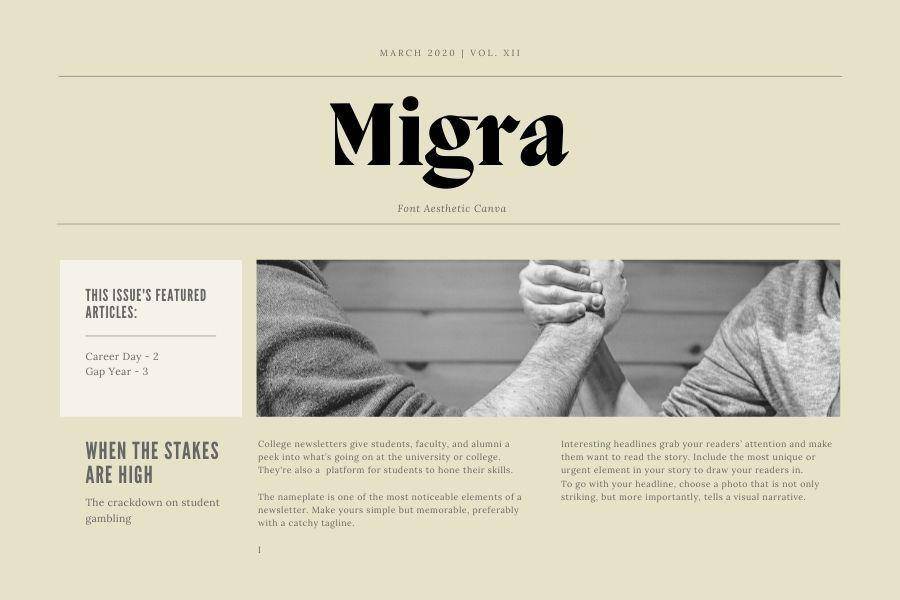
Mengawali list font aesthetic Canva dengan jenis serif yang 'old but gold'. Font ini persis yang digunakan pada koran jadul. Meski memiliki kaki, Migra masih mudah dibaca dan cocok untuk badan teks yang membutuhkan kesan tradisional. Ada dua bobot font tersedia, lalu bisa menerapkan aturan italic, bold, maupun underline juga.
2. Anaktoria
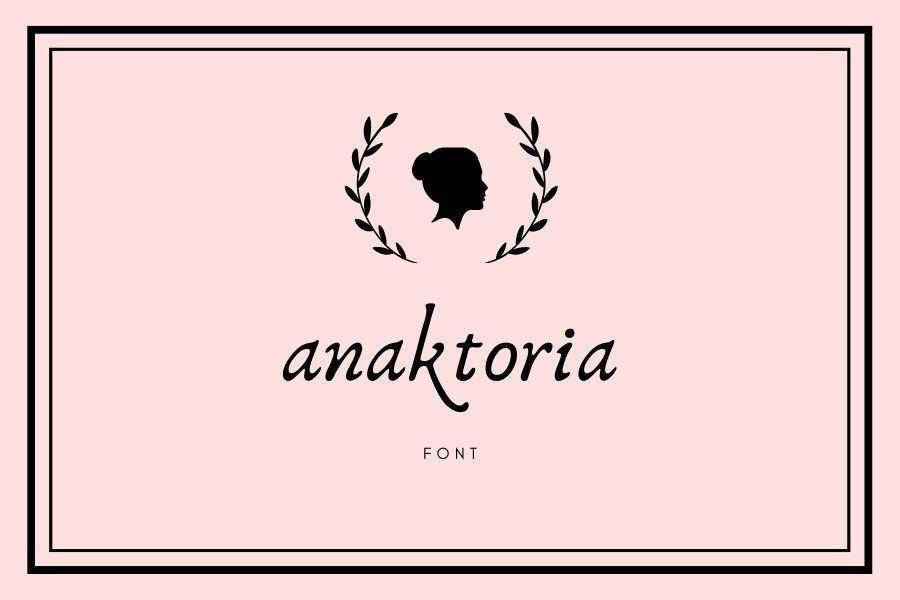
Butuh handwritting font yang gak neko-neko? Anaktoria bisa kamu gunakan untuk desainmu. Font ini mengusung karakter huruf bersambung, tapi gak bersambung mirip tulisan tangan. Anaktoria pun memiliki aksen yang bisa meningkatkan visual desain.
3. Kollektif
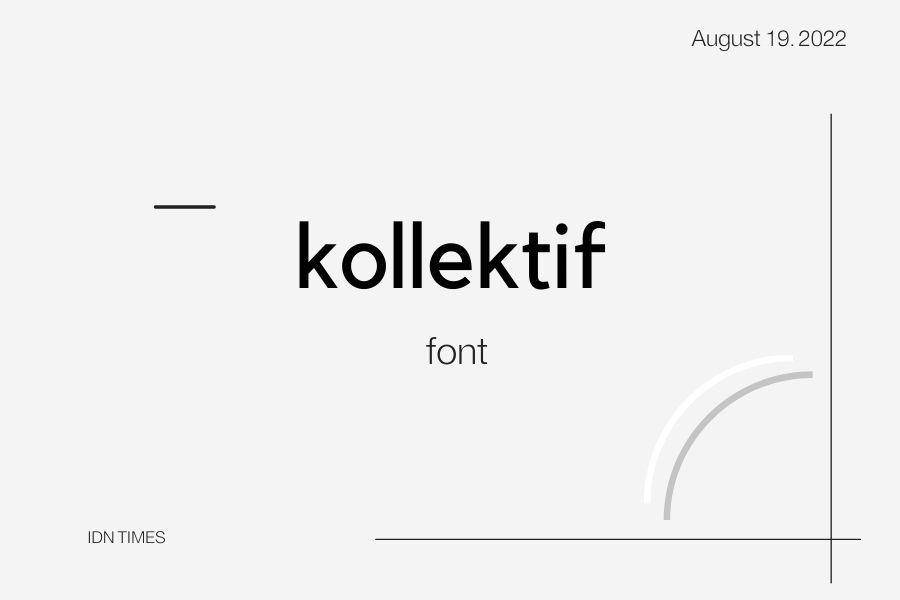
Font bersih dan minimalis ini sangat nyaman dipandang. Dengan ujung tegas tanpa ekor, Kollektif memberikan kesan to the point. Mudah dibaca, tapi gak kaku-kaku amat, mau dibuat judul, head, ataupun badan teks, Kollektif tetap oke.
4. Megrim
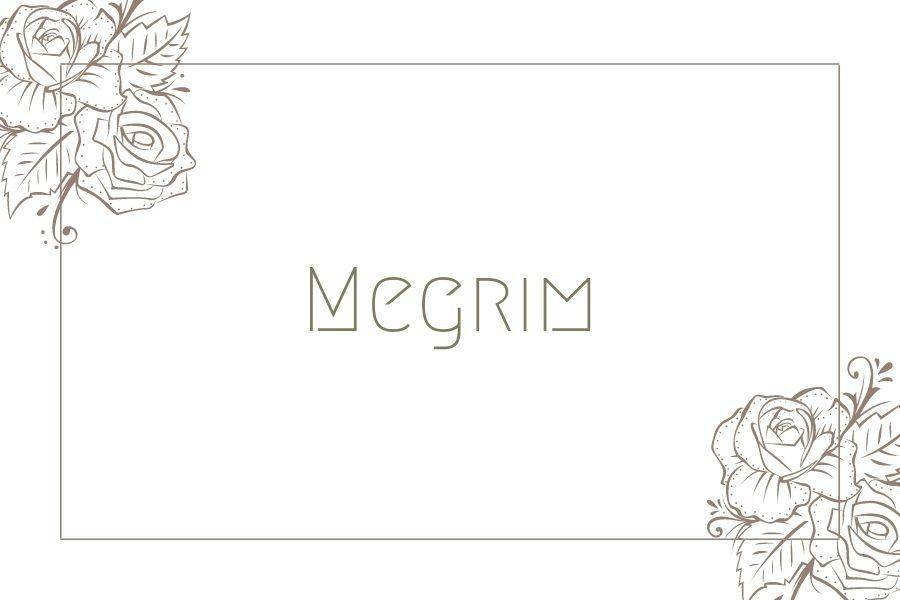
Ingin font unik, tapi tetap mudah dibaca? Megrim oke untuk dipadukan dengan gambar maupun ilustrasi. Font ini mengusung struktur geometris yang tegas, tapi memiliki tambahan style yang bisa membuat desainmu lebih unik. Cocok untuk judul yang menuntut atensi lebih.
5. Linux Biolinum
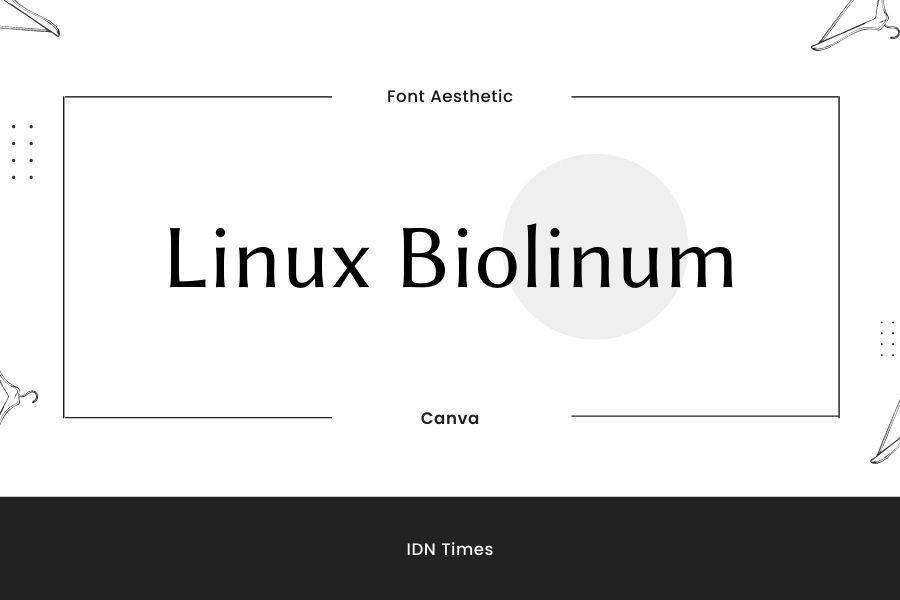
Desain font ini merupakan jenis Sans-Serif dengan layar berbasis modul. Bentuknya memanjang dan tertutup, serta memiliki x-height yang tinggi. Secara default, font tersusun rapat sehingga terkesan slim dan gak memakan ruang. Spasinya membuat kesan renggang dan mudah dibaca.
6. VAL
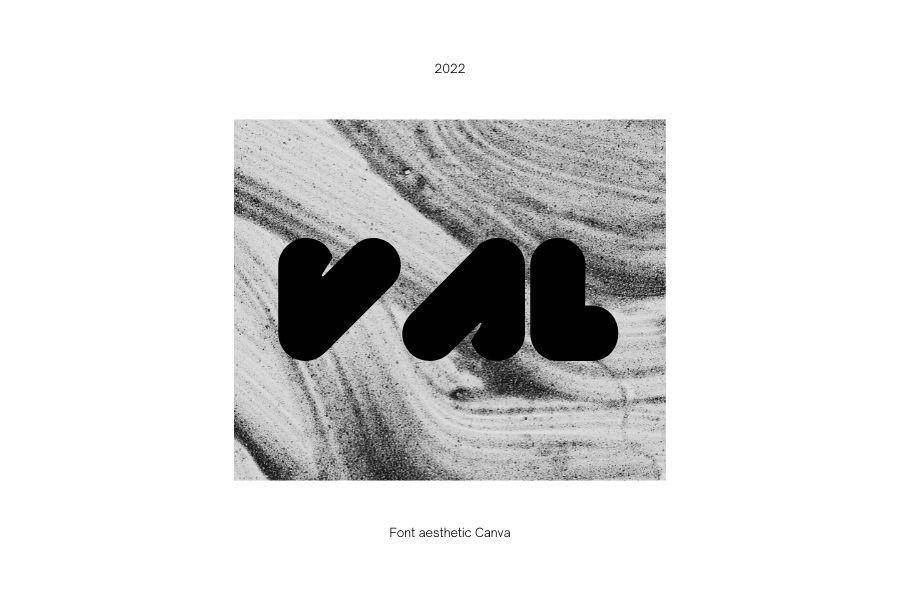
Dari namanya, sekilas bikin teringat brand produk laki-laki, gak, sih? Well, font ini bersifat modern, minimalis, dan membulat. Semakin unik, pembuat menyisipkan seni tulisan dengan memiringkan sebagian sisi huruf yang cocok jadi pilihan font aesthetic Canva.
7. Giaza
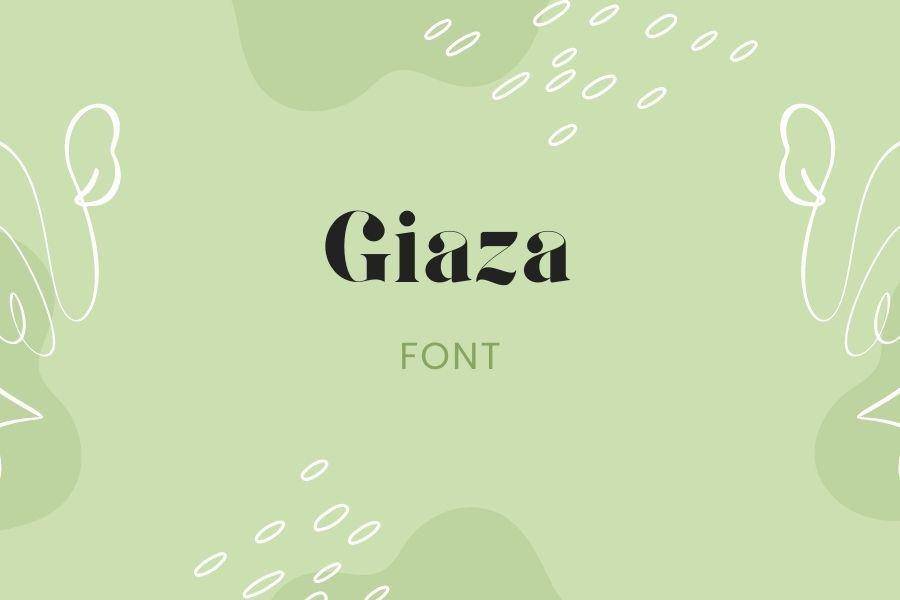
Butuh font aesthetic Canva yang masuk jenis Serif, tapi gak kuno? Giaza bisa jadi solusi. Giaza merupakan jenis huruf terbaca dan bersih. Mengonsep huruf dengan ketebalan sisi yang berbeda, cocok untuk memberikan kesan tegas, tapi gak kaku. Ciamik, bukan?
8. Dreaming Outloud
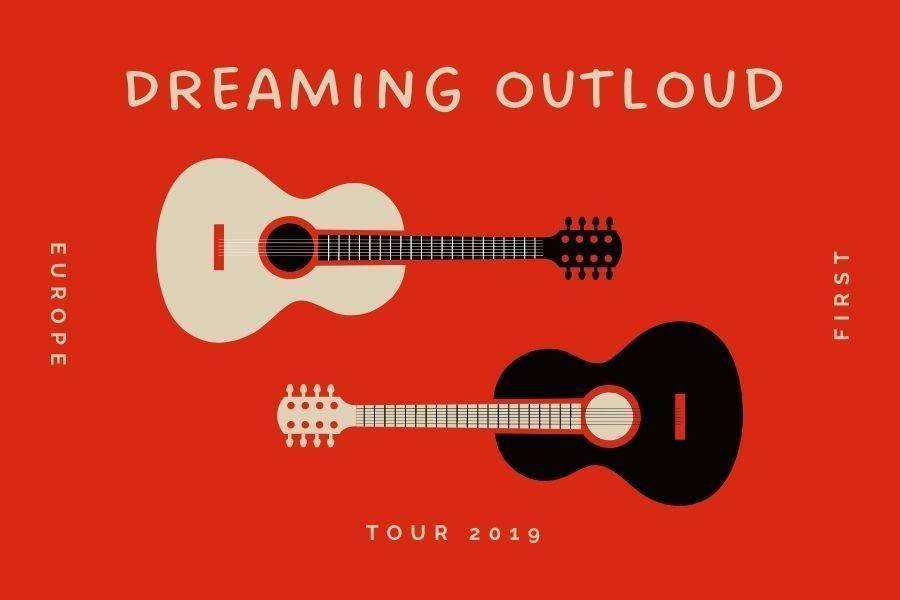
Poster musik sering menggunakan font sesuai genre konsernya. Nah, font Dreaming Outloud merupakan pilihan yang cocok. Merupakan font kapital, membuat masing-masing huruf memiliki tinggi dan lebar yang sama. Meski terkesan gak formal, font ini tetap memberikan kesan jelas.
9. Bugaki
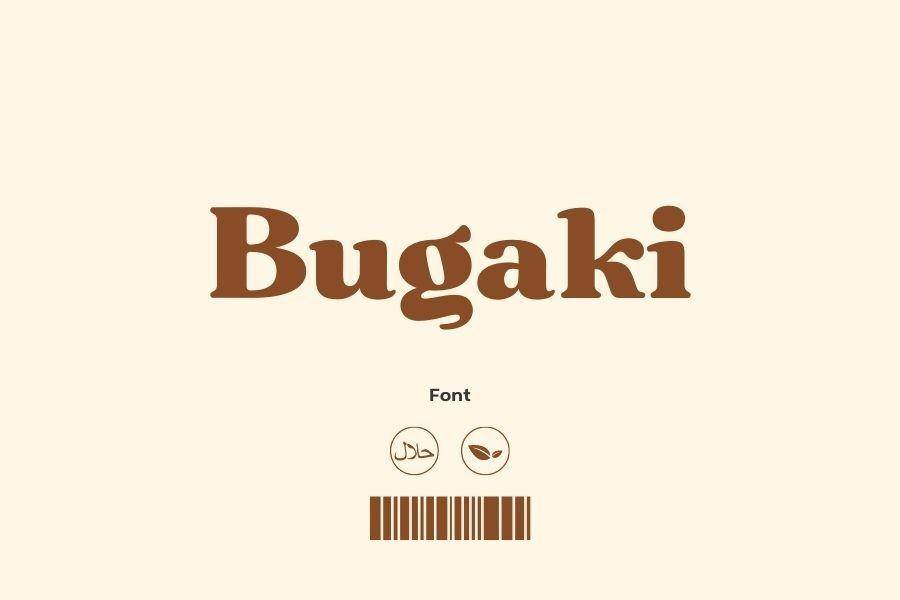
Ada juga font aesthetic Canva yang memberikan desain berbeda saat digunakan dalam huruf kapital dan huruf kecil, salah satunya Bugaki. Font ini membawa kesan bold, tetapi dengan sentuhan tebal tipis yang menawan. Bentuk huruf tersusun secara melingkar, ringan, serta gak menghilangkan kesan elegan.
10. Donau
Kalau membutuhkan font dengan seluruh huruf kapital yang unik nan aesthetic, bisa pakai font Donau. Font ini mengusung tema huruf besar yang slim dan rapat. Desainnya sangat cocok digunakan baik sebagai headline, judul, bahkan tulisan utama pada poster.
11. Creative Vintage Draft
Kadang font bisa sangat membosankan, tapi, say no more dengan adanya Creative Vintage Stamp. Di dalamnya, menyisipkan alternatif bentuk font yang memukau. Belum lagi style ala-ala stamp yang bergaya vintage. Cocok buat desain grafis ataupun logo yang bertema santai.
Kalau kamu bingung mengombinasikan font aesthetic Canva di atas, kamu bisa menggunakan saran yang disediakan oleh Canva. Sudah, deh, waktunya berkreasi mix and match!